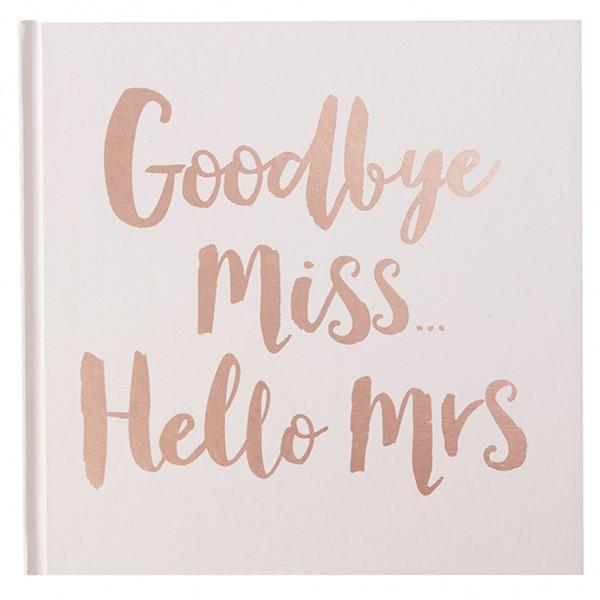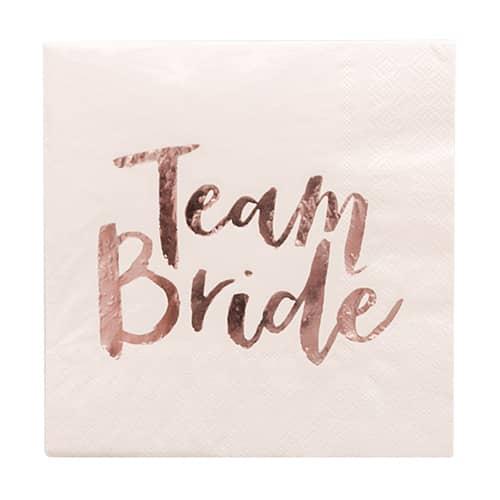
Ich suche diese Schriftart von Junggesellinnenabschiedspartys Zubehör
Ich möchte ein JGA Fotobuch gestalten und suche diese Schriftart.
Diese Schriftart ist auf Servietten, T-Shirts, Strohhalmen und Büchern zu finden sobald man Team Bride auf Google eingibt.
Also hier ein Beispiel für Servietten mit dieser Schrift:
Dort findet man den Verweis auf die Herkunft: Brand: Ginger Ray
Suche moderne Schreibschrift/Pinselschrift von Hühnchenrennen T-Hemden von Ginger Ray
Muss es genau diese Schrift sein? Es gibt da einiges in der Richtung, teilweise auch als freie Schriften. Diese Art von Schriften ist irgendwann mal in der Mitte dieser Dekade ziemlich Modern geworden.
Diese Art von Schriften ist irgendwann mal in der Mitte dieser Dekade ziemlich Modern geworden.
Ok das ist nur meine subjektive Meinung, aber für mich sehen die alle  irgend wie gleich aus (ok nicht wirklich) aber  übersehen hab ich sie mir  schon.
Die erste freie Schrift die ich damals gefunden habe war die Selima von Befonts:
Da lief die Welle aber schon eine Weile. Diese ging von den kurz vorher hypermodernen schmalen Markerschriften in SmallCaps/AllCaps aus und über. Das muss so 2015 rum gewesen sein? Ich habe das in meiner Betrachtung zu diesen schmalen Markerschriften und deren Modewelle dann angehängt. Daher habe ich auf eine echt freie Schrift für das Setzen von Beispielen gewartet und danach gezielt gesucht. Das Dokument könnte ich echt noch mal ein bisschen überarbeiten. Hier die letzte Version von 2017:  Studie_CC.pdf